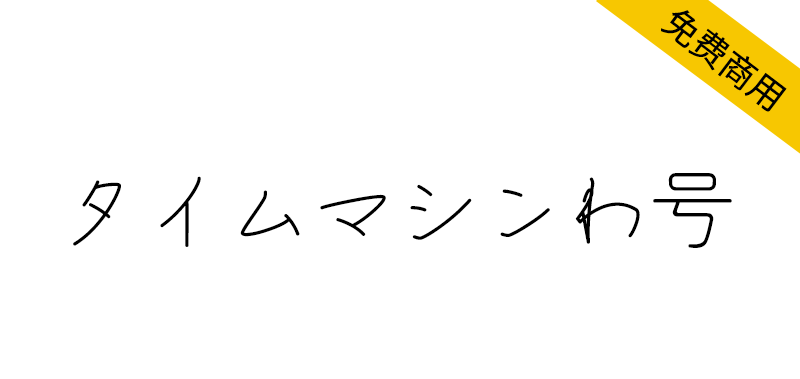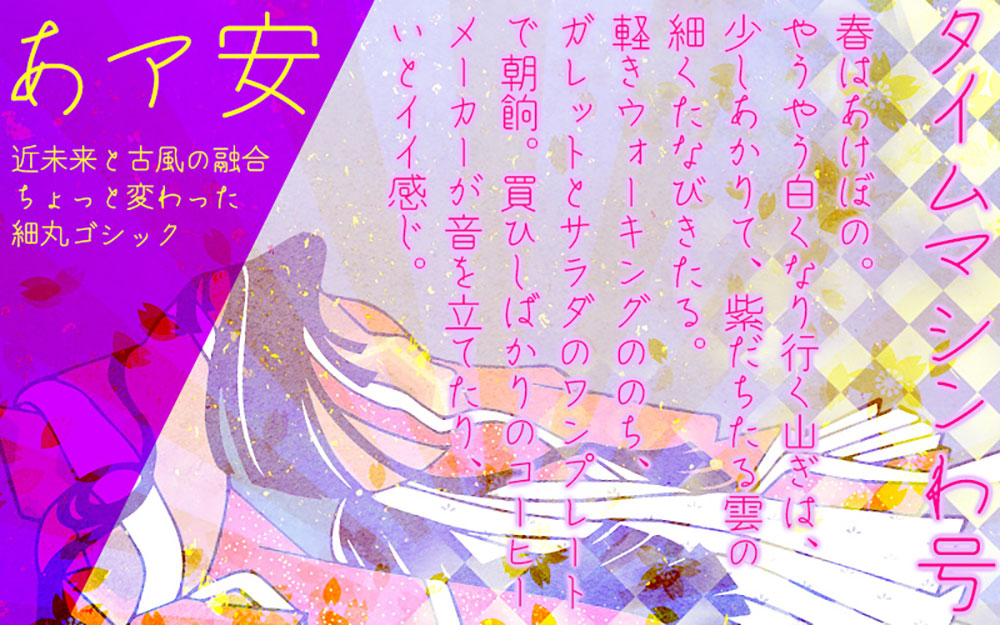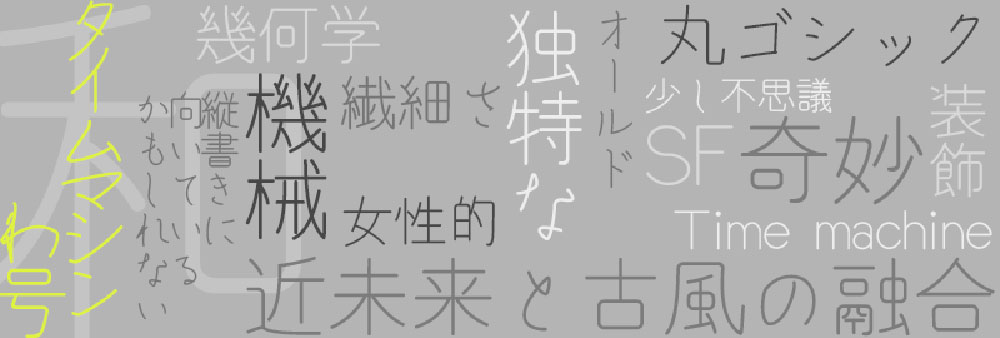
タイムマシンわ号是和田研細丸ゴシック衍生字体,以和田研細丸ゴシック2004绘文字(稀土元素)为基础,将原创的假名组合起来,整理而成。向和田研フォント及び、和田研細丸ゴシック相关人员表示深深的感谢。在算法半自动生成的独特汉字中发现了科幻感,结合完全相反的古风假名,让气氛变得更加不可思议。
和田研細丸ゴシック派生フォントです。「和田研細丸ゴシック2004絵文字(希土類元素レアアース様)」を元に、オリジナルのかなを組み合わせ、アレンジしたものです。和田研フォント及び、和田研細丸ゴシック関係者各位に深く御礼申し上げます。アルゴリズムによって半自動的に生成されたという、独特な漢字にSF感を見出し、真逆の古風なかなを合わせて、より不思議な雰囲気にしてみました。